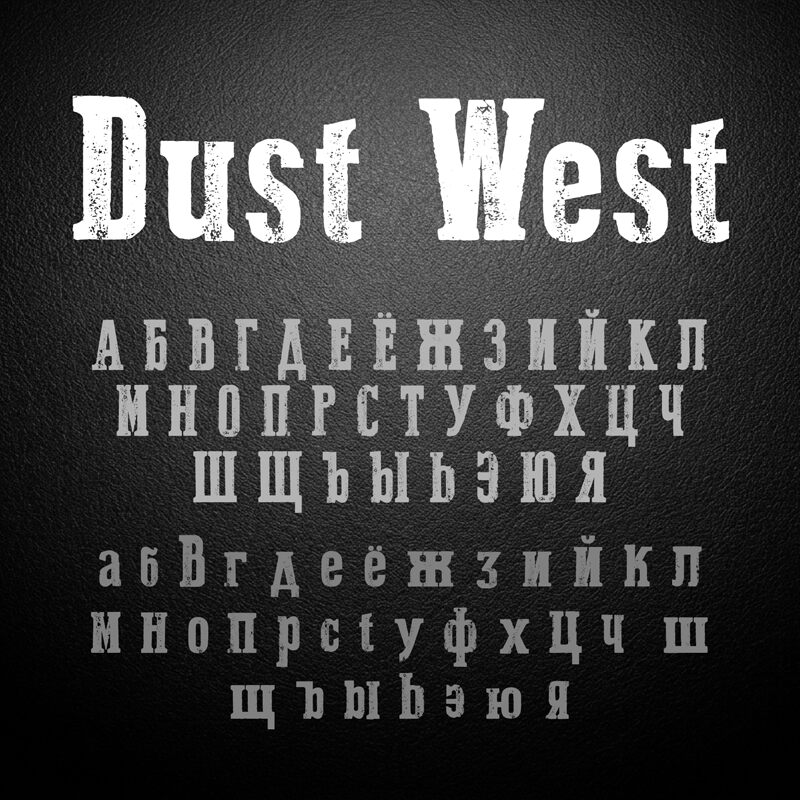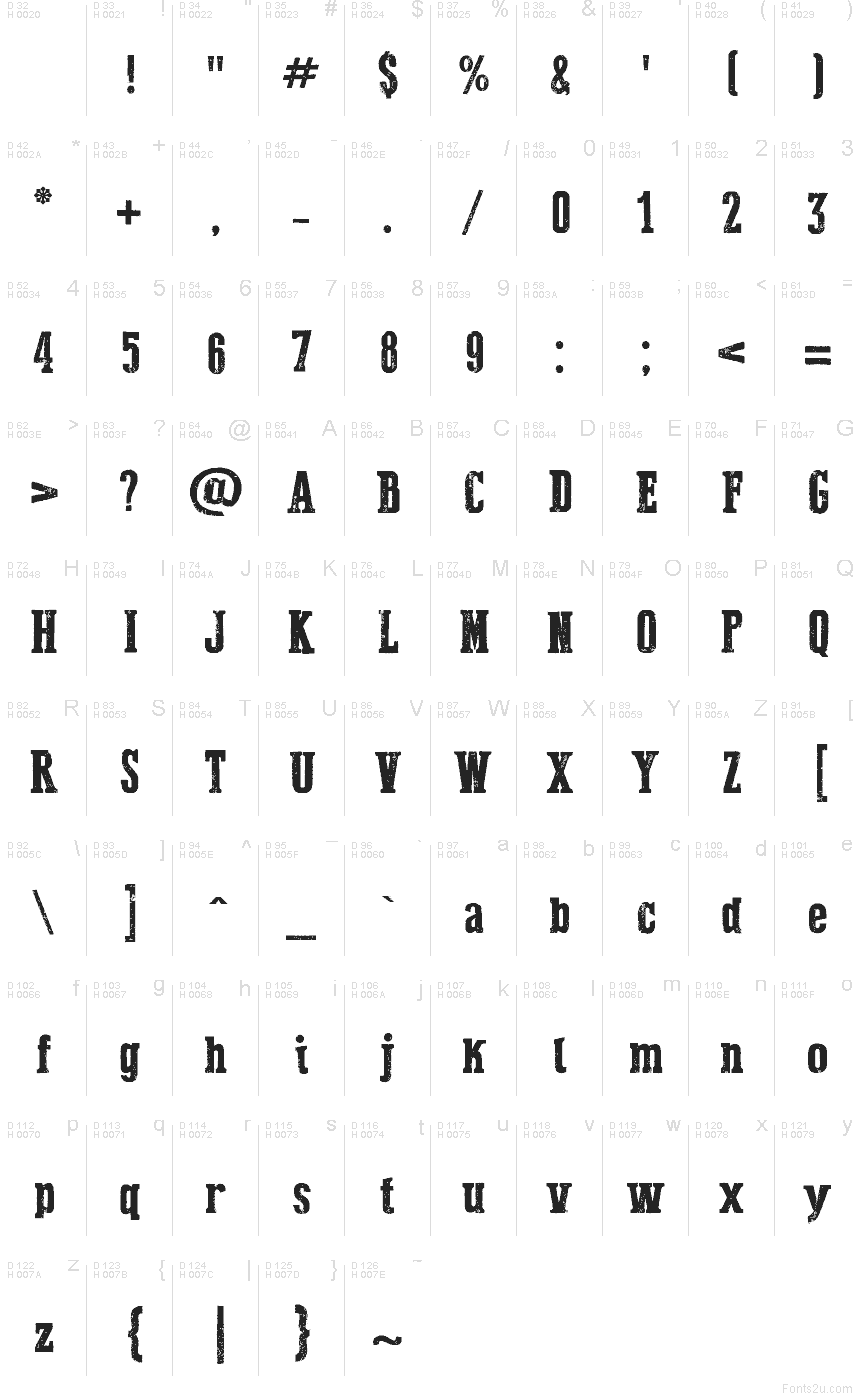
Dust West Regular
Dust West od Galdino Otten je bezplatné westernové display písmo, ktoré v sebe nesie drsný, prachom pokrytý pocit starého dreveného typu z plagátov divokého západu. Jeho robustné písmená využívajú výrazné pätky a hlboké známky opotrebovania, takže celá abeceda vyzerá, ako by bola roky tlačená, používaná a vystavená vplyvom počasia.
To z neho robí prirodzenú voľbu pre branding v štýle saloonu, etikety na whisky, rodeo letáky, obaly s tematikou Americana či festivalové plagáty, kde textúra dotvára príbeh. Ako bezplatný font funguje skvele aj pre krátke nadpisy, titulky a logotypy, pretože ošúchaná textúra dodá aj pár slovám tú pravú atmosféru starého západu.